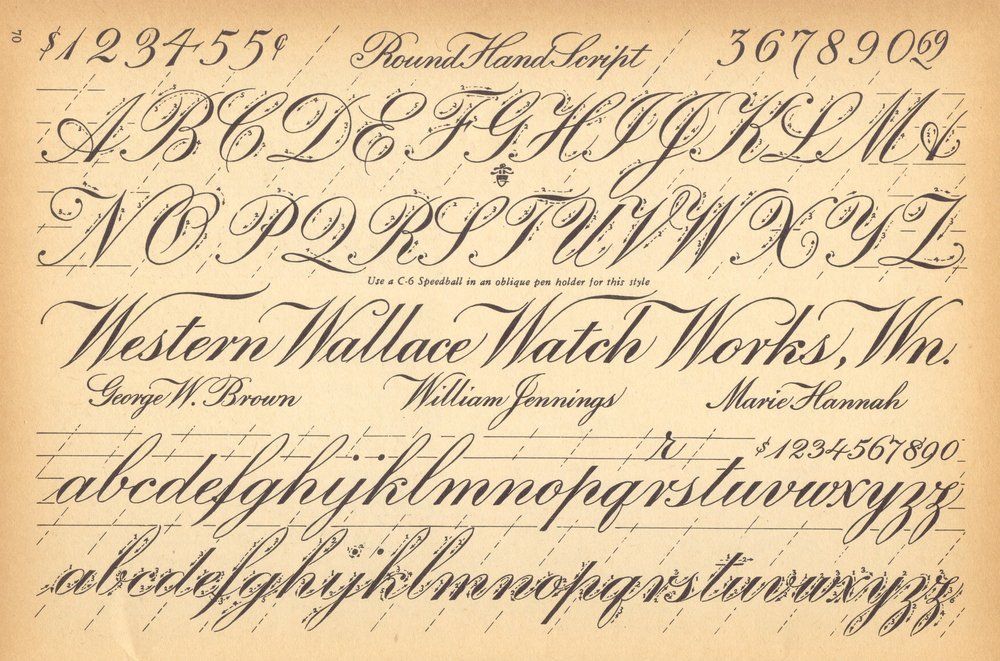
Какой шрифт лучше на памятник из гранита — образцы гравировки в Москве
Как выбрать шрифт для памятника?
Есть несколько критериев, которые надо учитывать при выборе шрифта:
- Шрифт на памятнике должен быть легко читаемым. Поэтому, для гравировки на черном граните подойдут любые шрифты, а на цветном или пестром лучше выбрать моношрифт без засечек. Так же гравированную надпись можно покрыть золотой, серебряной, черной краской и она будет гораздо ярче смотреться.
- Шрифт должен быть красивым и вписываться в общий дизайн памятника. Для женских памятников больше подходят рукописные шрифты или шрифты с засечками, для мужских брусковые моношрифты.
- Современные шрифты, которые были изобретены для компьютеров. Подойдут для надписи на памятниках молодым людям.
- Для памятника с березкой на могилу бабушке или дедушке можно выбрать старославянские шрифты.
Условно шрифты можно разделить на несколько групп:
- с засечками;
- без засечек;
- моношрифты — буквы одной ширины;
- рукописные;
- современные;
Каллиграфия. Рукописные шрифты Запада и Востока 73
144 ДРУГИЕ ВИДЫ ПИСЬМА
СТРОЧНЫЕ БУКВЫ КИРИЛЛИЦЫ
Как и в большинстве романских языков, кириллический шрифт включает
в себя как прописные, так и строчные буквы. Многие из этих букв покажутся
говорящему и пишущему по-английски человеку хорошо знакомыми,
хотя произносятся эти буквы совсем не так, как в английском языке.
С
овременный печатный кириллический шрифт берет на¬
чало от шрифта, приніггого еще при царе Петре I, — этот
графских литер.
Известный как «гражданский шрифт», онприменяется и в наши дни для печатания «светских» книг, в
то время как в богослужебной литературе продолжают ис¬
пользовать более древний, близкий к готическому шрифт.
Показанный ниже алфавит — это рукописный вариант
гражданского шрифта, который широко используется для
плакатов и объявлений. В советский период таким шрифтом
писали стенгазеты, — они всегда делались от руки, поскольку
в СССР все типографии были государственными и печатае¬
мая в них продукция проходила строжайшую цензуру. При
этом властям удалось достичь парадоксального эффекта, —
благодаря стенгазетам и рукописным объявлениям многие
советские граждане научились писать красиво и разборчиво.
В средневековой России официальные и деловые доку¬
менты писали шрифтом, который был неудобочитаемым
для русского глаза, — это объясняется тем, что тогдашние
писцы брали за образец шрифты, которыми пользовались в
странах Западной Европы.
Наконец, в XVIII веке появилась
производная от шрифта «копперплейт» форма русского кур¬
сивного письма, которая стала основой современного рус¬
а б б г д есжз
А Бэ
Вэ
Гэ Дэ
Е Ё
Жэ Зэ
и
К
Л
М Н О
И И краткое
Ка
Эль
Эм
Эн 0
п р
С
TJ
/
X ц
Пэ Эр
Эс
Тэ
У Эф
Ха Цэ
Ч Ш 1
ш.
Ъ Ы
Ь Э
ю я
Че Ша
Ща
Твердый знак Ы
Мягкий знак Э оборотное
ю я
В таблице приведены названия строчных букв русского алфавита
РУССКАЯ КИРИЛЛИЦА 145
Пишем букву «б»
1 Держа перо под накло¬
ном приблизительно 45°,
проведите плоскую, накло¬
ненную влево дугу, начав ее
от верхней линии строки и за¬
кончив небольшим поворо¬
строки.
2 Приложите перо к началь¬
ной точке первого штриха и
проведите слегка изогнутую
вправо линию вдоль верхней
Итак, если вы попытаетесь написать несколько страниц печатными буквами — это займет огромное количество времени и сил. Курсив пишется намного быстрее и легче.
Сейчас, когда компьютеры и принтеры получили широкое распространение, вам не нужно так много писать. Но все же в некоторых районах компьютеры редкость и вам, скорее всего, придется писать там какие-то документы по старинке.